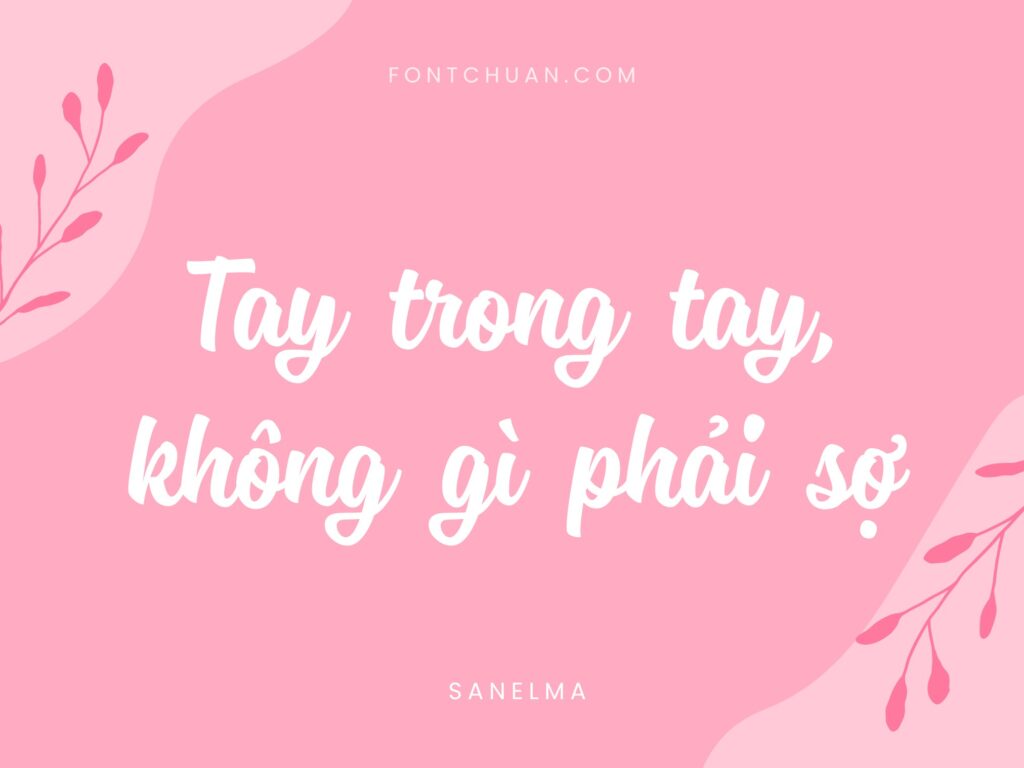
Font iCiel Sanelma Việt Hóa
Sanelma là một kiểu chữ viết tay bằng cọ, lấy cảm hứng từ nghệ thuật vẽ biển hiệu và chữ viết trên xe Hot Rod. Được thiết kế bởi Mika Melvas và phát hành vào năm 2014, Sanelma mang đến cảm giác mượt mà, linh hoạt và tự nhiên cho các thiết kế. Đặc biệt, Sanelma đã được Việt hóa bởi iCiel, hỗ trợ tiếng Việt cùng nhiều ngôn ngữ khác, đáp ứng nhu cầu đa dạng của người dùng. Thành viên của Font Chuẩn đã sưu tầm và chia sẻ font này, giúp cộng đồng thiết kế ứng dụng dễ dàng trong các dự án của mình.
Về đặc điểm thiết kế, Sanelma sở hữu hơn 1.200 ký tự với nhiều biến thể, bao gồm các ký tự thay thế, swash và chữ hoa nhỏ, cho phép tùy chỉnh linh hoạt trong thiết kế. Font này phù hợp cho các dự án như logo, bao bì sản phẩm, tiêu đề và biển hiệu cần sự nổi bật và cá tính. Ngoài ra, Sanelma còn thích hợp cho các ngành nghề như quảng cáo, ẩm thực, thiệp cưới và spa, cùng các sự kiện đặc biệt như lễ hội, sinh nhật, Valentine và Trung thu.